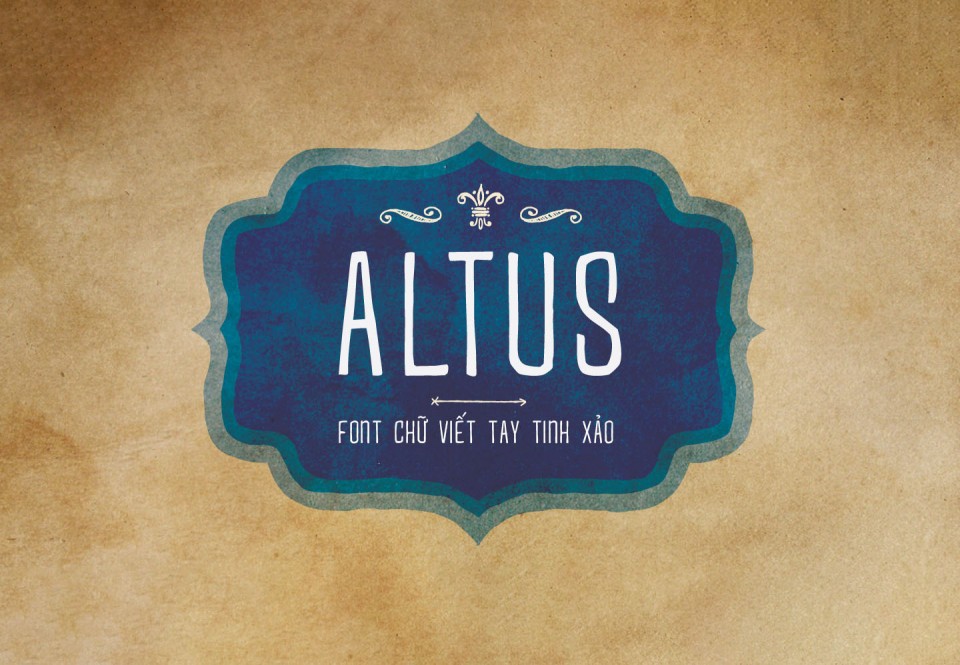
Font việt hóa iCiel Altus – Bộ font sang trọng cho thiết kế hiện đại
Giới thiệu về bộ Font việt hóa iCiel Altus
Trong thế giới sáng tạo, việc lựa chọn một Font Chữ phù hợp là yếu tố then chốt giúp truyền tải thông điệp hiệu quả. Font việt hóa iCiel Altus nổi lên như một sự lựa chọn hàng đầu cho những ai tìm kiếm vẻ đẹp thanh lịch và tinh tế. Đây là một bộ font sans-serif được thiết kế với những đường nét tối giản nhưng không kém phần hiện đại, đặc biệt phù hợp cho các bạn học sinh và sinh viên trong việc trình bày báo cáo hoặc làm slide thuyết trình tại nhà trường. Nhờ quá trình việt hóa chỉn chu, người dùng có thể hoàn toàn yên tâm khi gõ tiếng Việt mà không lo gặp lỗi hiển thị hay mất dấu.
Ưu điểm nổi bật của Font việt hóa iCiel Altus
Thiết kế đa dụng và chuyên nghiệp
iCiel Altus sở hữu cấu trúc hình học cân đối, tạo cảm giác dễ nhìn và chuyên nghiệp. Với nhiều biến thể từ nét mảnh đến nét đậm, bộ font này cho phép người dùng linh hoạt trong việc tạo điểm nhấn cho tiêu đề hoặc trình bày nội dung chi tiết. Đối với các thầy cô giáo, việc sử dụng bộ font này trong giáo án giúp văn bản trở nên khoa học và thu hút sự chú ý của học sinh hơn.
Tương thích cao với nhiều phần mềm
Kết luận và trải nghiệm Font việt hóa iCiel Altus
Tóm lại, đây là một công cụ hỗ trợ đắc lực giúp nâng tầm giá trị thẩm mỹ cho mọi tác phẩm đồ họa và tài liệu học tập. Nếu bạn đang tìm kiếm một giải pháp Typography chất lượng, hãy thử ngay Font Miễn Phí, Font Việt Hóa, Font việt hóa iCiel Altus để cảm nhận sự khác biệt trong từng nét chữ. Chúc các bạn có những trải nghiệm thiết kế tuyệt vời và đầy cảm hứng sáng tạo mỗi ngày.